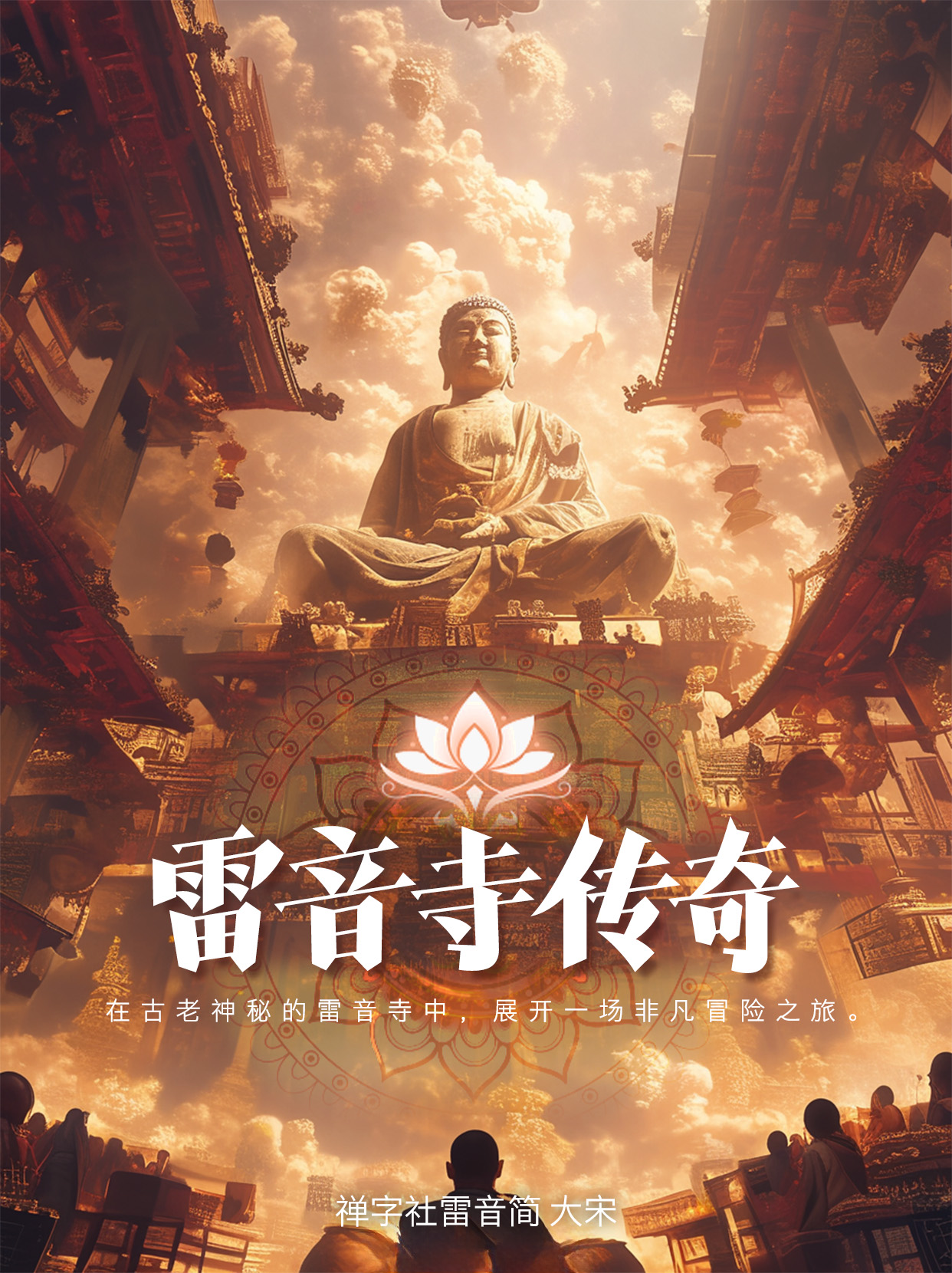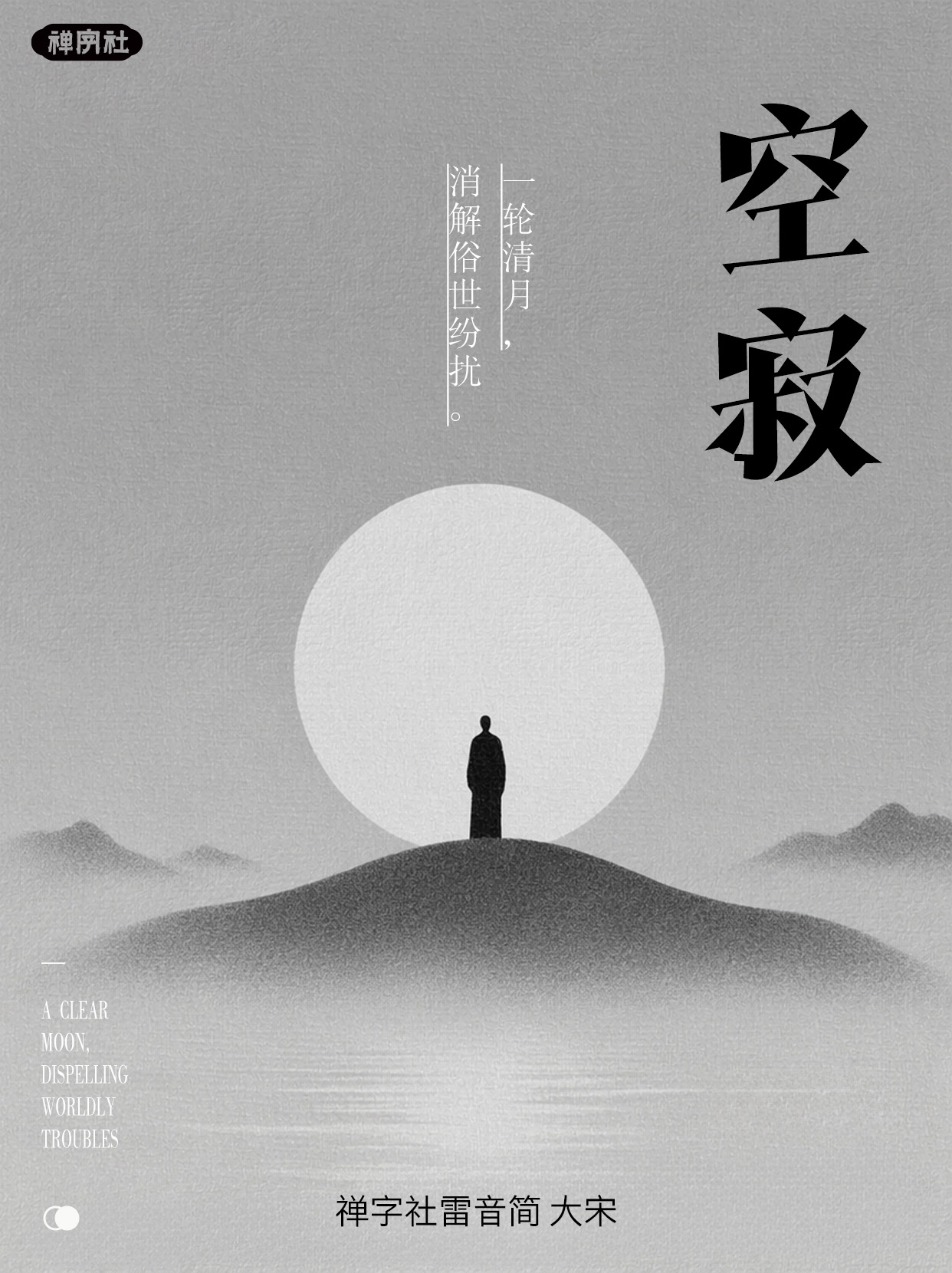
禅字社雷音简 大宋
禅字社雷音简 大宋是一款将刻本字体进行创新的创意宋体,既有庄重挺拔有不失国潮新意。 字体以楷为骨,整体向右上倾斜,结体紧凑险绝,字形长而不窄、舒展有型。以宋为肉,其笔画作为标题字而言灰度适中,笔画线条硬挺,细节中随处都可见锋利的刀刻线条,一眼刻入人心,如天鼓雷音警戒人心,但巧妙融合充满国潮新意的造型,例如勾与口部件的造型,充满现代潮流感。适用于产品包装、广告标题、海报宣传、招牌等应用场景。